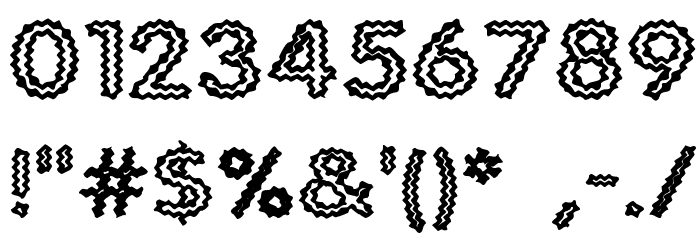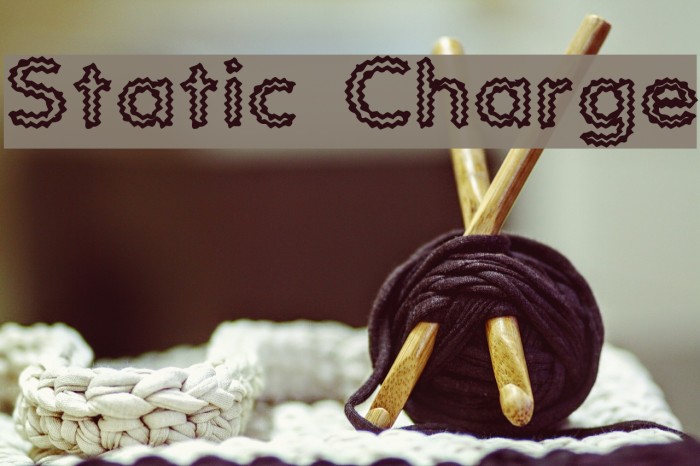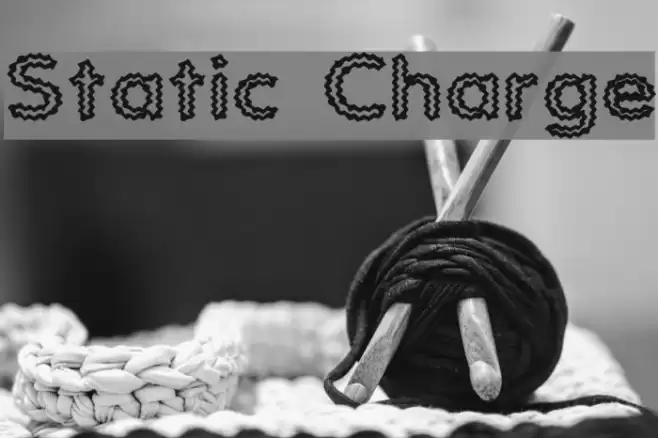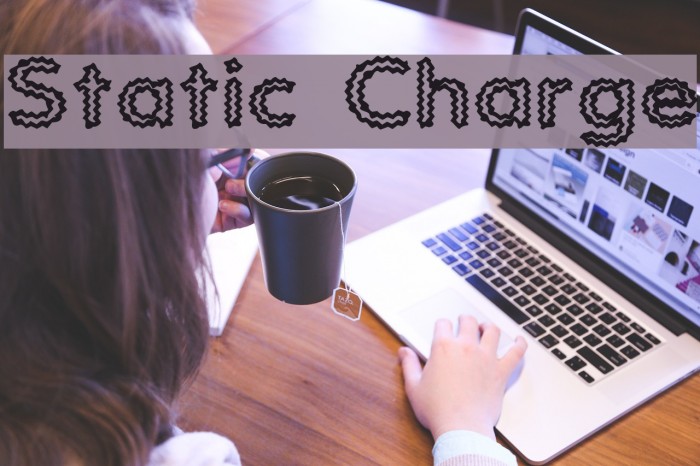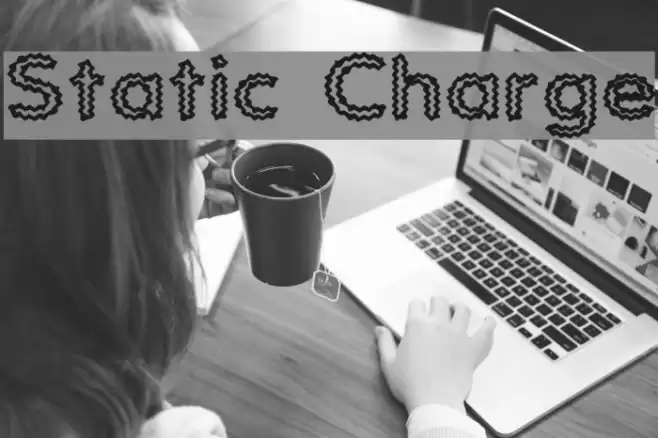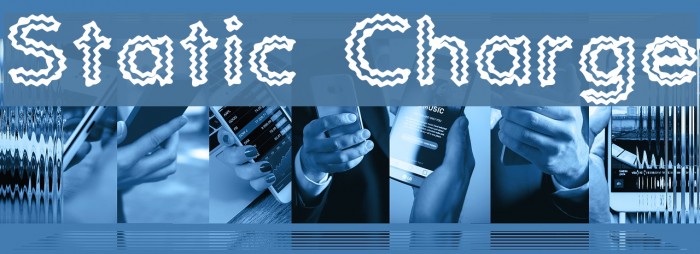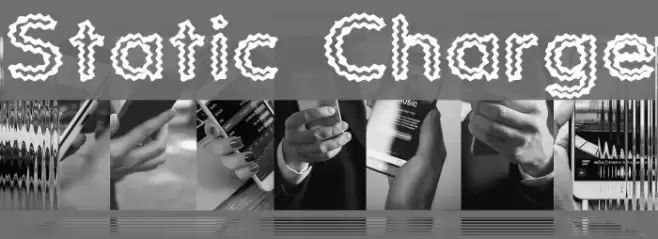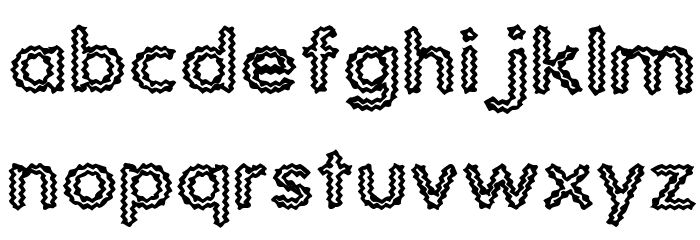
Static Charge Font
| Vorgeschlagene Projekte | Ideal for projects that require a bold and eye-catching design, such as posters, event flyers, album covers, or branding for creative industries. |